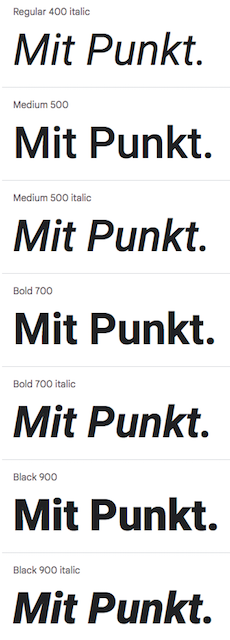
[Mitglied Held…] Geschrieben 28. Januar Teilen Geschrieben 28. Januar Hallo liebe Freunde, ich habe die Schriftart "Roboto" installiert und habe auf dem Mac damit gestaltet. Die Punkte sollten eigentlich quadratisch sein, allerdings werden diese dann Rund. Bei der Installation der Schrift werden diese auch quadratisch angezeigt, allerings im Textprogramm wiederrum rund. Wie kann ich es schaffen das auch in den grafikprogrammen dies punkte quadratisch angezeigt werden? Link zu diesem Kommentar
[Mitglied R::b…] Geschrieben 28. Januar Teilen Geschrieben 28. Januar Vorsichtshalber erstmal die naheliegende Nachfrage: Kann man ausschließen, dass mehrere Versionen der Roboto auf dem Rechner liegen und ggf. eine andere aktiviert bzw. verwendet wurde? Edit: Du sprichst zunächst vom Mac aber der Screenshot sieht eher nach einem anderen Betriebssystem aus. Wichtig für das gewünschte Ergebnis ist eben, dass Du auf allen Systemen die selbe Version der Roboto verwendest, da diese tatsächlich in unterschiedlichen Ausführungen existiert. Link zu diesem Kommentar
[Mitglied Held…] Geschrieben 28. Januar Themen-Ersteller Teilen Geschrieben 28. Januar Das Problem liegt tasächlich auf beiden Systemen gleich. Anscheinend tatsächlich die Version Link zu diesem Kommentar
[Mitglied Norb…] Geschrieben 28. Januar Teilen Geschrieben 28. Januar Hm, links ist es kursiv, rechts gerade … hat evtl. nur der Kursiv-Schnitt die runden Punkte? (Was auf einen Versionen-Mischmasch hindeuten würde.) Die aktuelle Version hat jedenfalls runde Punkte … (die Version von 2013, die ich gerade noch irgendwo rumliegen hatte, hat eckige Punkte). 2 Link zu diesem Kommentar